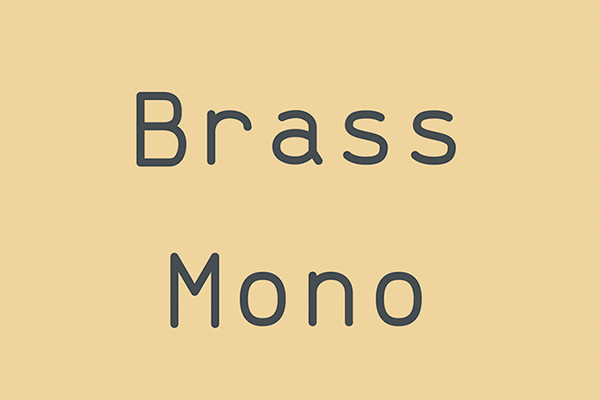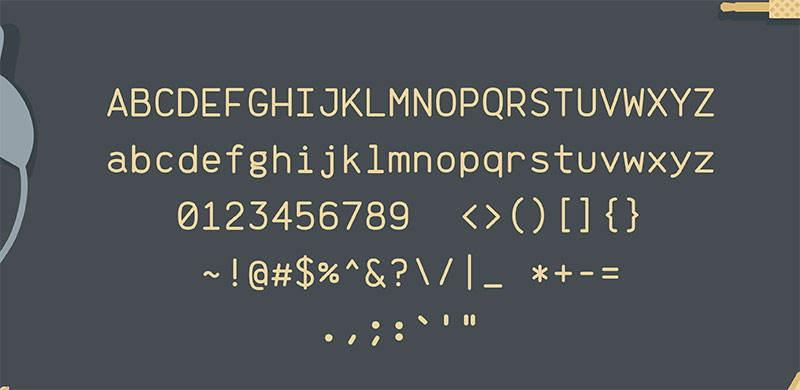
Brass Mono
这款免费的复古等宽圆角英文字体,灵感源自70年代的电气和机械设计,别具一格。它在Github上开源,您可以下载源文件自由使用,本站已经将其导出并打包提供下载,该字体提供3种不同的字体宽度(间距),无论是在进行排版还是商用,都能为您提供更好的选择。
Brass Mono 效果预览
Brass Mono 字体效果预览